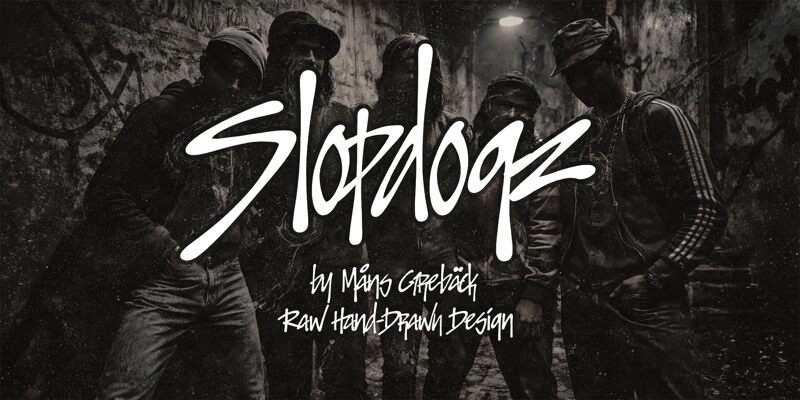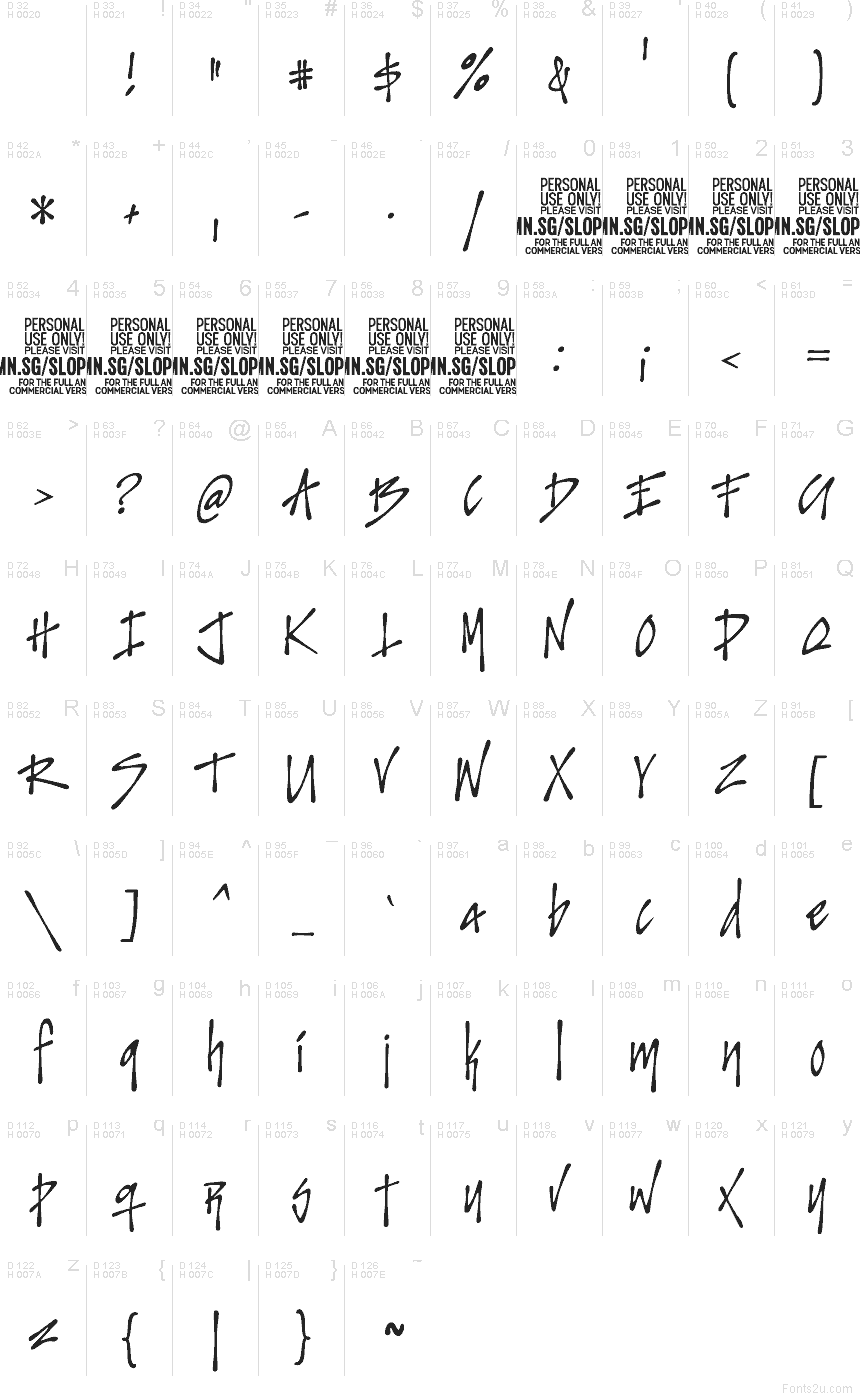
Slopdogz PERSONAL USE Regular
Slopdogz di Mans Greback AB è un font script in stile graffiti gratuito, che cattura la spontaneità di un tag fatto velocemente con il pennarello. Le lettere sono alte, strette e inquiete, con tratti lunghi, angoli vivi e un ritmo irregolare che rende il design come scarabocchiato sul momento, piuttosto che studiato a tavolino.
È perfetto per il branding streetwear, poster musicali, grafiche da skateboard, fanzine e titoli dove il tocco grezzo e scritto a mano conta più della rifinitura. Essendo un font gratuito, funziona bene anche per titoli brevi, copertine e bozze di loghi, poiché le verticali allungate e gli agganci bruschi regalano anche a poche lettere un'energia autentica e dirompente.